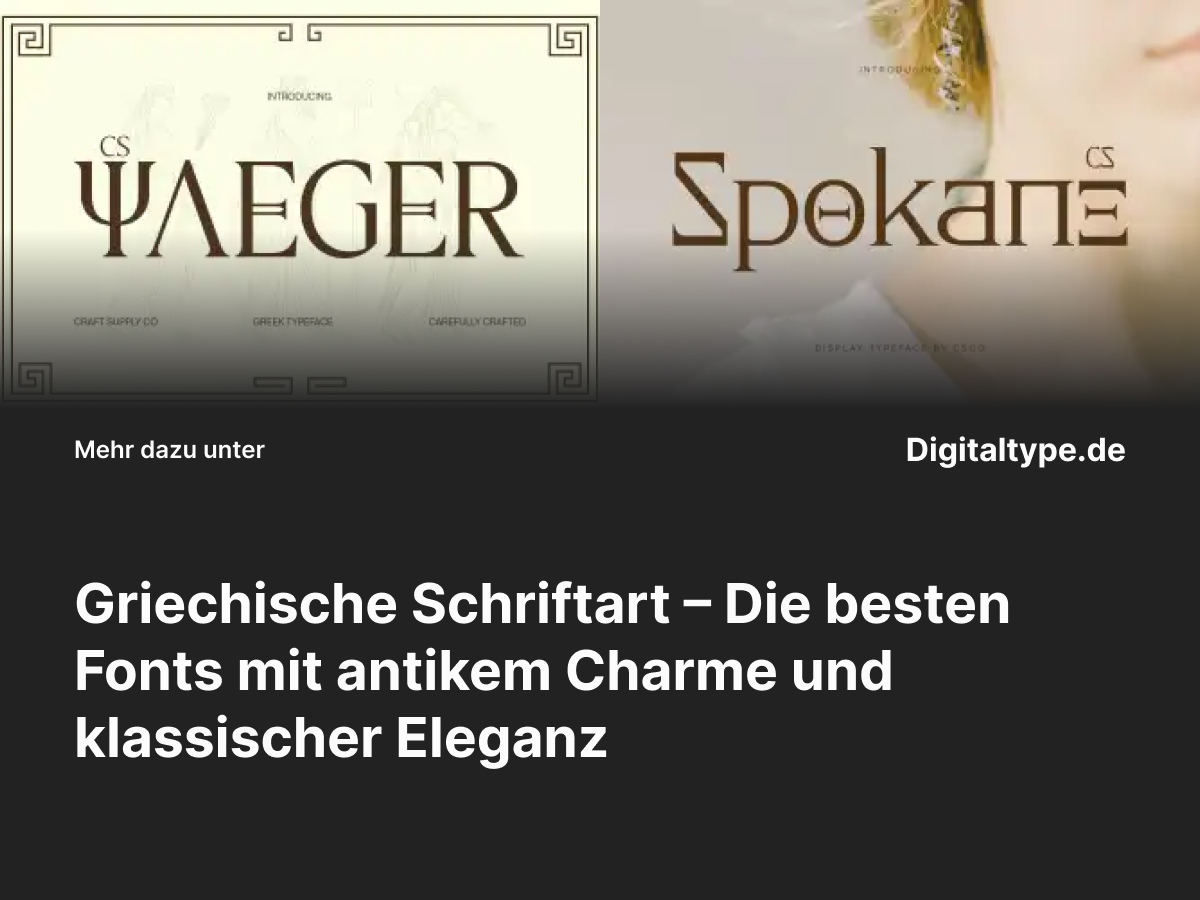
Die griechische Schriftart ist bekannt für ihre markanten Formen, kunstvollen Linien und den unverwechselbaren historischen Charakter. Inspiriert von der antiken griechischen Typografie und Architektur, verleihen diese Fonts jedem Design einen Hauch von Klassik, Kultur und Mythologie. Ob für Logos, Filmplakate, Restaurants oder Luxusmarken – griechische Schriftarten erzeugen sofort Assoziationen mit Geschichte, Wissen und Ästhetik. In diesem Artikel zeigen wir dir, was diese Schriften auszeichnet und stellen dir sechs herausragende Alternativen vor.
Was ist eine griechische Schriftart?
Eine griechische Schriftart basiert auf der klassischen Ästhetik des griechischen Alphabets – mit klaren, geometrischen Formen, scharfen Serifen und einer Balance zwischen Eleganz und Stabilität. Oft findet man sie in Museen, Filmplakaten oder Markenlogos, die an antike Zivilisationen, Philosophie oder Mythologie erinnern. Diese Fonts transportieren Geschichte und Prestige – ein Gefühl, das sofort Aufmerksamkeit erzeugt.
Griechische Fonts sind nicht nur für klassische Themen geeignet, sondern auch für moderne Branding-Projekte, die eine kulturelle Tiefe oder intellektuelle Wirkung erzielen wollen. Ihre Struktur wirkt stabil, gleichzeitig fein und majestätisch.
Wann du griechische Schriftarten verwenden solltest
- ✔️ Für Logos und Marken mit historischem oder kulturellem Bezug.
- ✔️ In Film- und Theaterprojekten mit antikem oder mythologischem Thema.
- ✔️ Für Restaurant- oder Produktdesigns mit mediterraner Identität.
- ✔️ In Print- oder Editorial-Designs, die Klassik und Eleganz kombinieren.
Eine griechische Schriftart kann deinem Design ein Gefühl von Erhabenheit und Geschichte verleihen – perfekt, wenn du visuelle Tiefe und Stärke ausdrücken möchtest.
Die 6 besten griechischen Schriftarten für Designer
Hier sind sechs sorgfältig ausgewählte griechische Schriftarten, die antike Schönheit mit moderner Typografie verbinden. Jede von ihnen bringt ein Stück Mythos, Geschichte und Eleganz in dein Design.
1. CS Yaeger Ancient Greek Font
CS Yaeger verkörpert klassische griechische Typografie mit moderner Präzision. Ihre klaren Linien und geometrischen Formen erinnern an antike Inschriften und Tempelbauten. Ideal für Branding, Logos oder Editorials mit historischer Tiefe.
2. CS Spokane Ancient Greek Font
CS Spokane ist eine elegante Serifenschrift, inspiriert von antiken Schriftzügen und Monumenten. Sie vereint Stärke mit Ästhetik – perfekt für Luxusmarken, Hotels oder kulturelle Projekte mit mediterranem Flair.
3. CS Olivera Greek Font
CS Olivera ist eine moderne Interpretation der griechischen Typografie. Mit weichen Kurven und ausgewogenen Proportionen eignet sie sich für elegante Designs – von Restaurant-Logos bis zu hochwertigen Verpackungen mit klassischem Stil.
4. CS Montera Greek Font
CS Montera verbindet antike Schriftästhetik mit zeitgemäßer Lesbarkeit. Diese griechische Schriftart wirkt majestätisch und professionell, ideal für Branding, Architekturprojekte oder akademische Publikationen.
5. CS Gelios Greek Font
CS Gelios ist eine stilvolle Serifenschrift, inspiriert von der Symbolik des antiken Griechenlands. Ihre feinen Linien und klaren Kanten schaffen eine elegante Typografie, die Autorität und Stil ausstrahlt. Perfekt für Logos, Buchcover oder Universitätsprojekte.
6. CS Elmore Ancient Greek Font
CS Elmore ist die perfekte Wahl, wenn du einen antiken, kunstvollen Look suchst. Ihre ausgeprägten Buchstabenformen erinnern an Steinmetzarbeiten aus der Antike. Diese griechische Schriftart ist ideal für Filme, Poster oder Branding mit historischem Thema.
Design-Tipps für griechische Schriftarten
- 1. Verwende dezente Farben: Gold, Weiß, Beige oder Dunkelblau betonen die klassische Eleganz griechischer Schriften.
- 2. Kombiniere mit klaren Sans-Serif-Fonts: So schaffst du Balance zwischen Antike und Moderne.
- 3. Nutze großzügige Abstände: Griechische Fonts wirken majestätischer mit mehr Raum zwischen den Buchstaben.
- 4. Setze sie in Titeln oder Logos ein: So entfalten sie ihre volle visuelle Wirkung.
Fazit: Griechische Schriftarten für klassische Eleganz und Stärke
Eine griechische Schriftart vereint Geschichte, Kunst und Design in einem. Sie bringt Würde, Intelligenz und Stil in jedes Projekt – von Logos über Magazine bis hin zu Filmplakaten.
Die vorgestellten Fonts spiegeln die Vielfalt griechischer Typografie wider – von authentisch antik bis modern inspiriert. Probiere sie in deinen Projekten aus und entdecke, wie sie deinem Design Tiefe und Bedeutung verleihen.